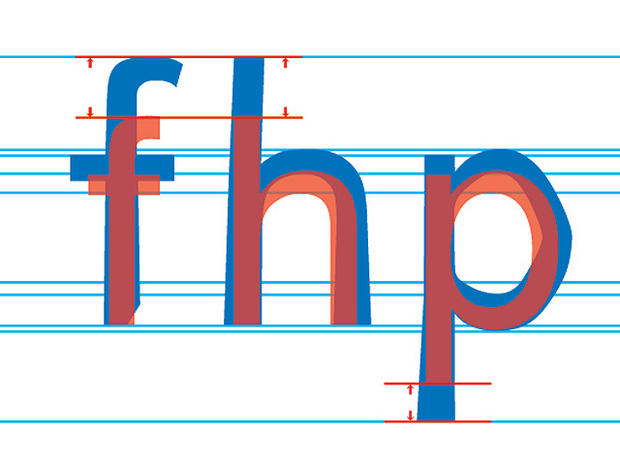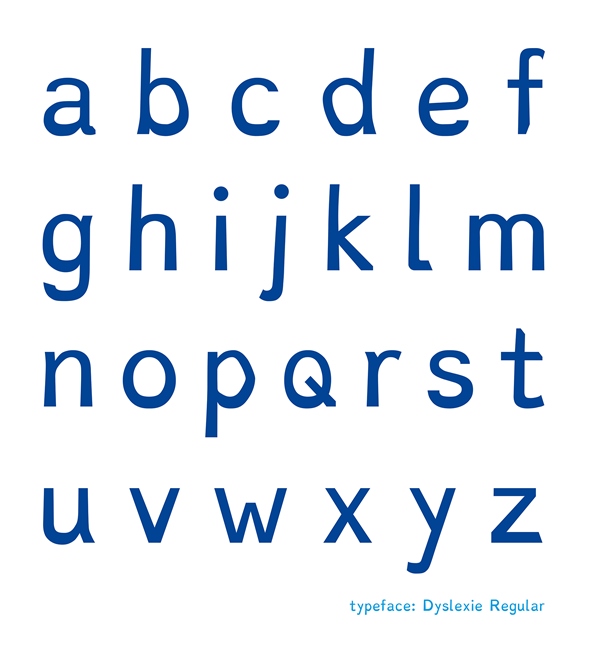
Uno de los trastornos de aprendizaje más conocidos en el mundo es la Dislexia que comúnmente afecta la lectura, compresión y ortografía.
Es por ello, que en 2008 el diseñador gráfico Christian Boer diseño Dyslexie, un sistema tipográfico creado especialmente para las personas que sufren de dislexia, ya que su diseño y uso eliminan los errores de lectura o dislexia más comunes como intercambiar, duplicar, cambiar, girar y fundir letras, ya que su estructura esta diseñada para que esto no suceda según las caracteristicas de este trastorno.
Dyslexie: un sistema tipográfico para quienes sufren dislexia
Con una forma única en cada una de sus letras Dyslexie permite a los usuarios leer sin problemas cualquier tipo de contenido mediante diversas extensiones para navegadores, archivos etc.